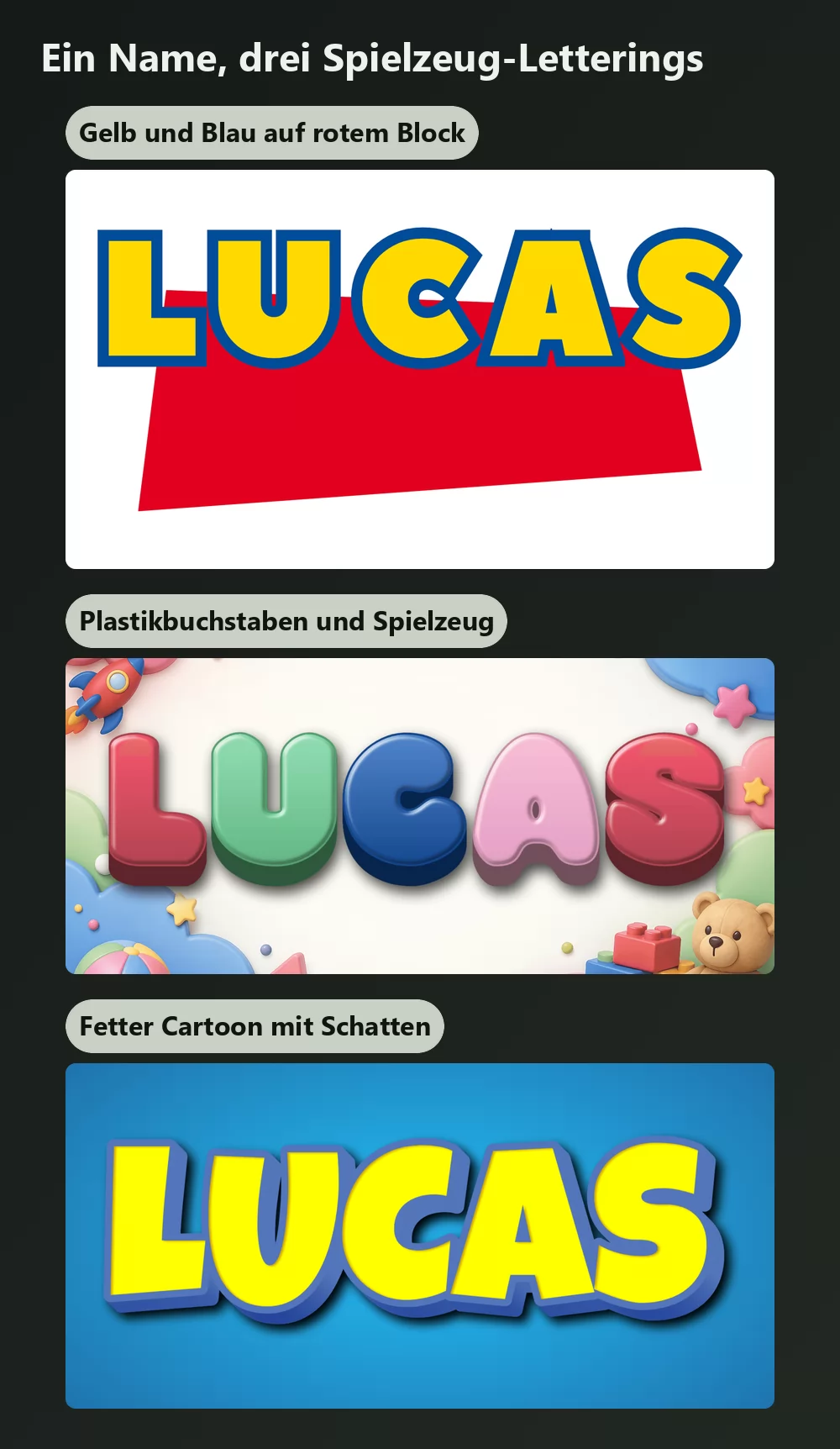
Suchen Sie nach der Toy-Story-Schrift, und Sie bekommen eine lange Liste von Downloads, die alle leicht falsch aussehen. Das ist kein Pech. Das Toy-Story-Logo ist keine Schrift, es sind zwei, und die meisten Downloadseiten geben Ihnen nur eine Annäherung an eine davon.
Die gute Nachricht: die andere Hälfte besitzen Sie womöglich längst, ordentlich lizenziert, ohne es zu wissen.
Das Logo besteht aus zwei Schriften, nicht aus einer
Das Wort «TOY» ist das dicke, runde Lettering, das alle vor Augen haben. Es wurde für den Film gezeichnet. Als Schriftart wurde es nie veröffentlicht, es gibt also nirgendwo eine legitime Datei davon.
Das Wort «STORY» ist das kleine Wort in der roten Form, und das ist eine echte, kommerziell erhältliche Schrift: Gill Sans Ultra Bold. Eric Gill zeichnete die Familie Gill Sans 1928 für Monotype; Ultra Bold ist der fetteste Schnitt, der hier verwendete.
Diese Teilung erklärt die Enttäuschung beim Download. Eine Datei namens «Toy Story Schrift» liefert Ihnen einen Doppelgänger der handgezeichneten Hälfte und nichts für die andere, dabei ist es das Zusammenspiel beider, das die Komposition trägt.
Die «TOY»-Hälfte wurde nie veröffentlicht, was gibt es also an Doppelgängern?
Immer wieder fallen die Namen Agent Red und Agent Orange von Pizzadude sowie SF Slapstick Comic. Sie treffen den Geist gut: fette, runde, leicht wacklige Versalien.
Eine Schriftlizenz ist keine Markenlizenz
Zwei getrennte Fragen, die ständig vermischt werden.
Selbst wenn Ihnen Gill Sans Ultra Bold vollständig gehört, deckt diese Lizenz die Buchstaben ab. Über Toy Story sagt sie nichts, und das ist Eigentum von Disney und Pixar; die Lizenz eines Doppelgängers sagt darüber ebenso wenig. Den Namen eines Freundes für ein Geburtstagsbanner in diesem Stil zu setzen, ist genau die private Nutzung, an der sich nie jemand gestört hat. Waren zu verkaufen, die von der Identität des Films leben, ist eine völlig andere Sache, und keine Schriftlizenz deckt Sie dabei.
Die praktische Grenze: personalisieren Sie frei für sich und Ihre Familie, und hören Sie vor allem auf, was Sie verkaufen oder womit Sie ein Geschäft bewerben.
Was den Look wirklich nach Toy Story aussehen lässt
Das ist der Teil, den die Downloadseiten überspringen, und er zählt mehr als die exakte Schrift. Vier Dinge leisten die Arbeit:
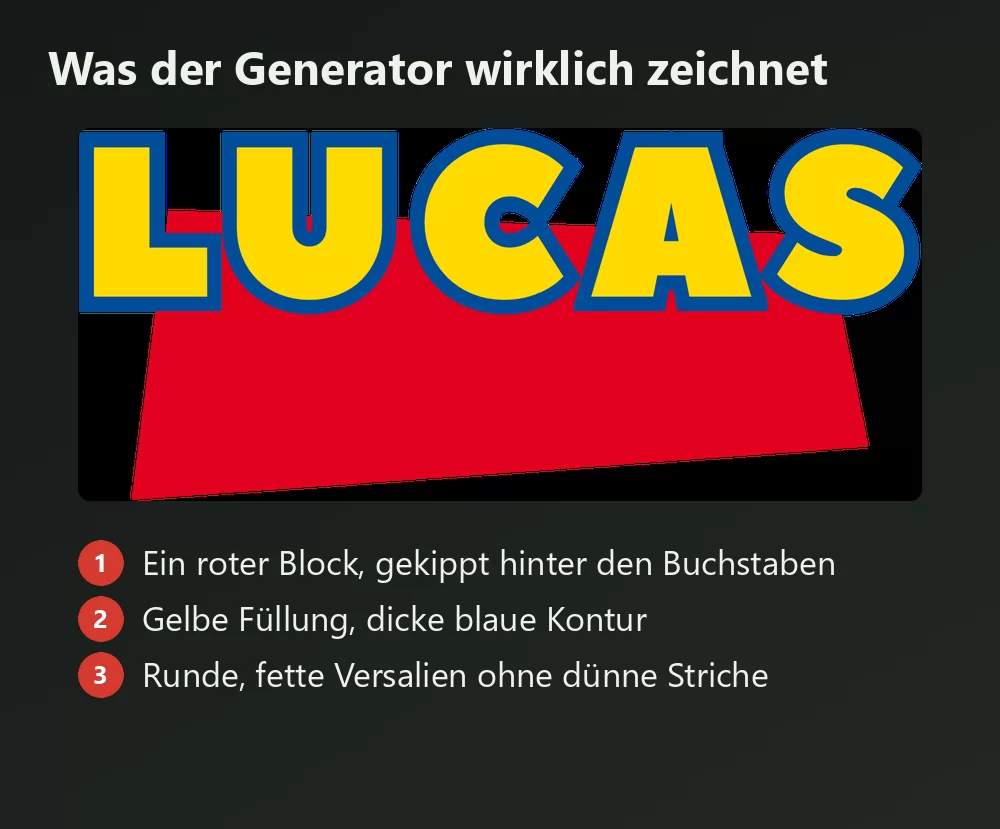
- Ein rotes Viereck, in eine Richtung gekippt, das hinter dem Titel als Farbfläche sitzt und nicht als sauberes Rechteck.
- Der Titel in die andere Richtung gekippt, sodass sich die beiden Winkel entgegenstehen. Diese Gegenneigung trägt fast die gesamte Energie der Komposition.
- Gelbe Füllung mit schwerer blauer Kontur, das Primärfarbenpaar, auf dem die ganze Reihe läuft.
- Leicht schief gesetzte Buchstaben, jeder in seinem eigenen kleinen Winkel, als hätte sie ein Kind hingelegt statt gesetzt.
Treffen Sie diese vier Punkte, sitzt der Look sogar mit einer ungefähren Schrift. Treffen Sie die Schrift exakt und lassen die Gegenneigung weg, erinnert nichts mehr an Toy Story.
Habe ich Gill Sans schon? Auf dem Mac ja. Mit installiertem Microsoft Office ja. Auf Windows ohne Office nein.
Welche Farben nutzt das Toy-Story-Logo? Gelbe Buchstaben mit blauer Kontur auf einem roten Block. Durchgehend kräftige Primärfarben, was zu einem großen Teil erklärt, warum der Look auf einen Blick erkennbar ist.